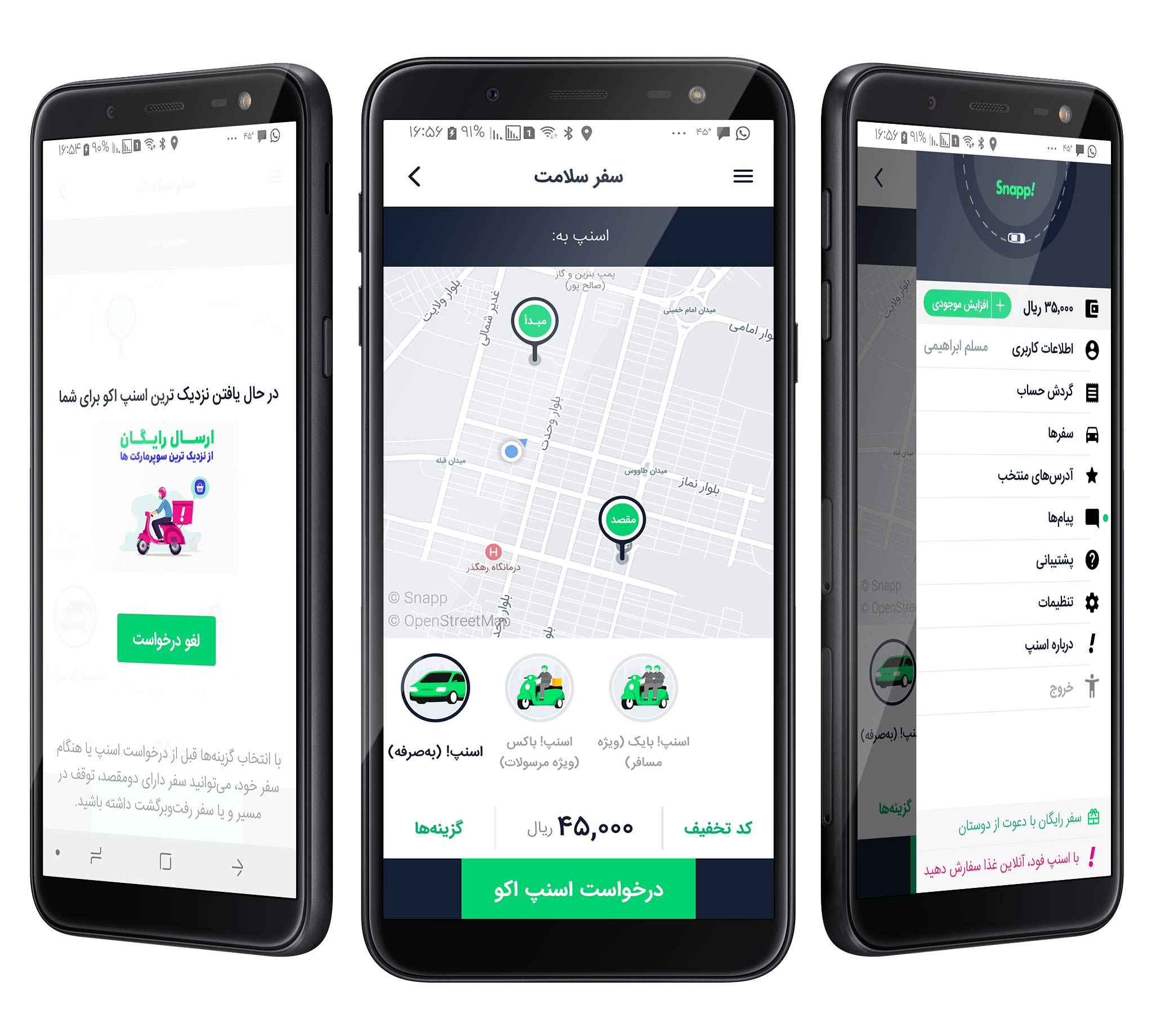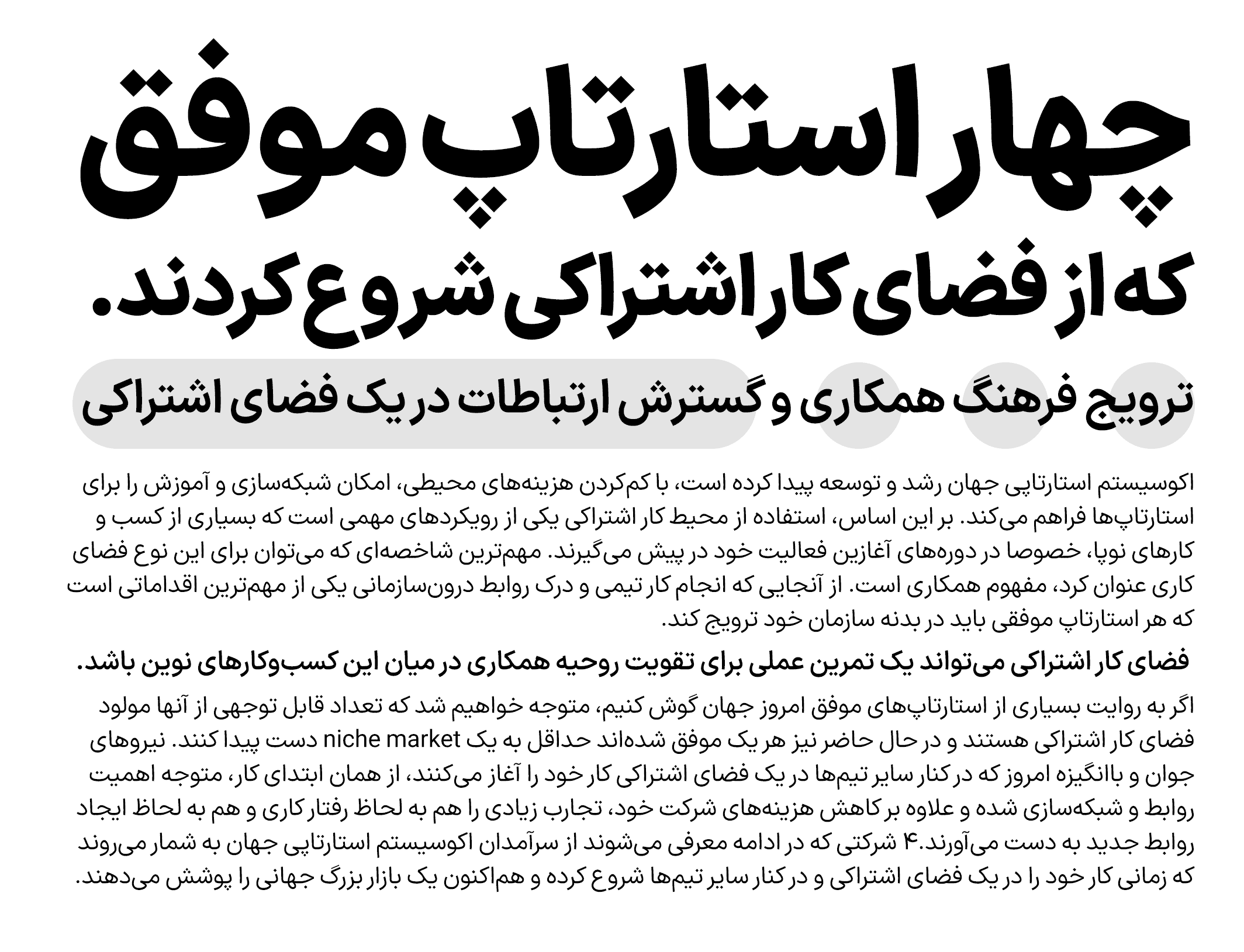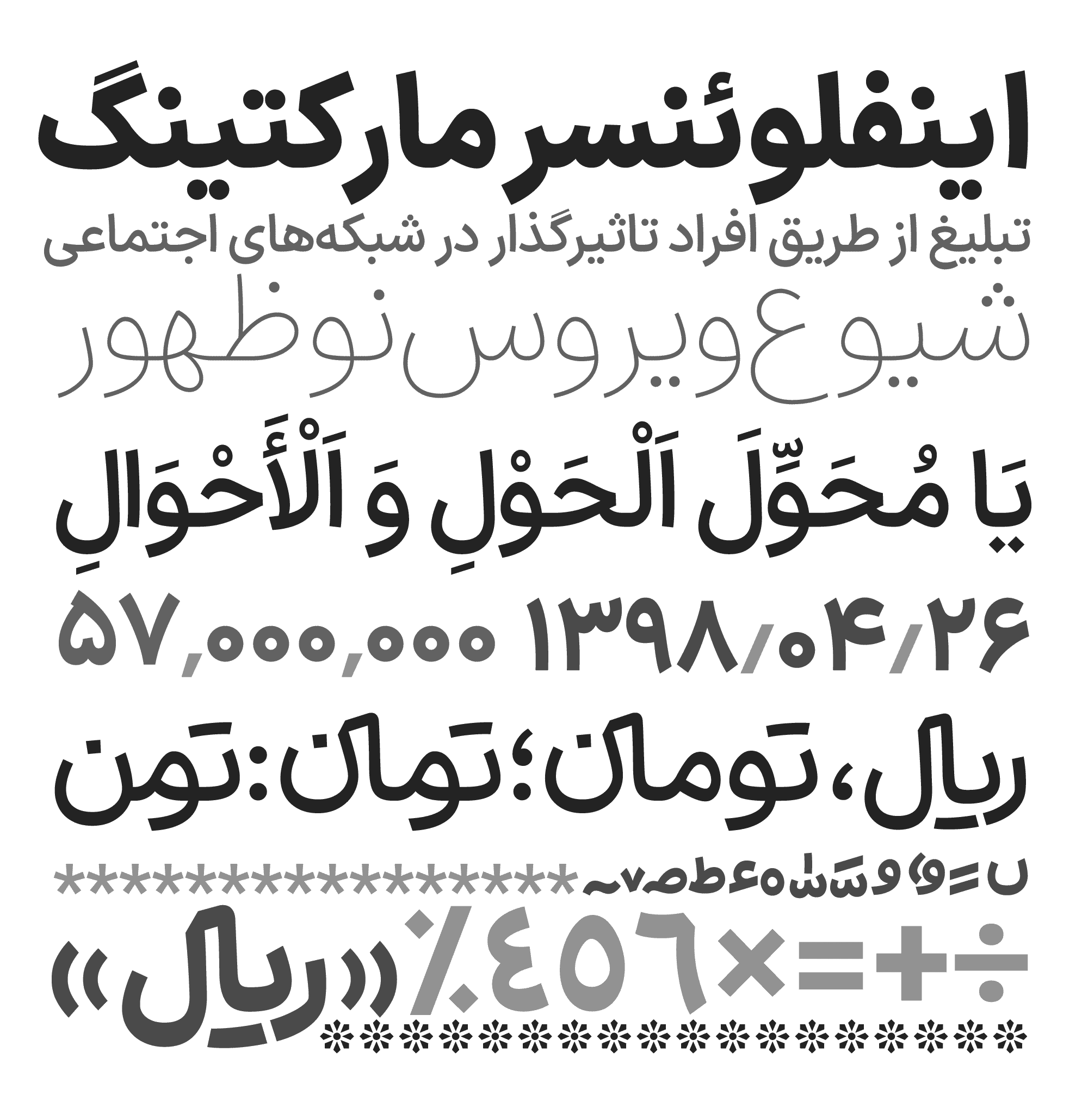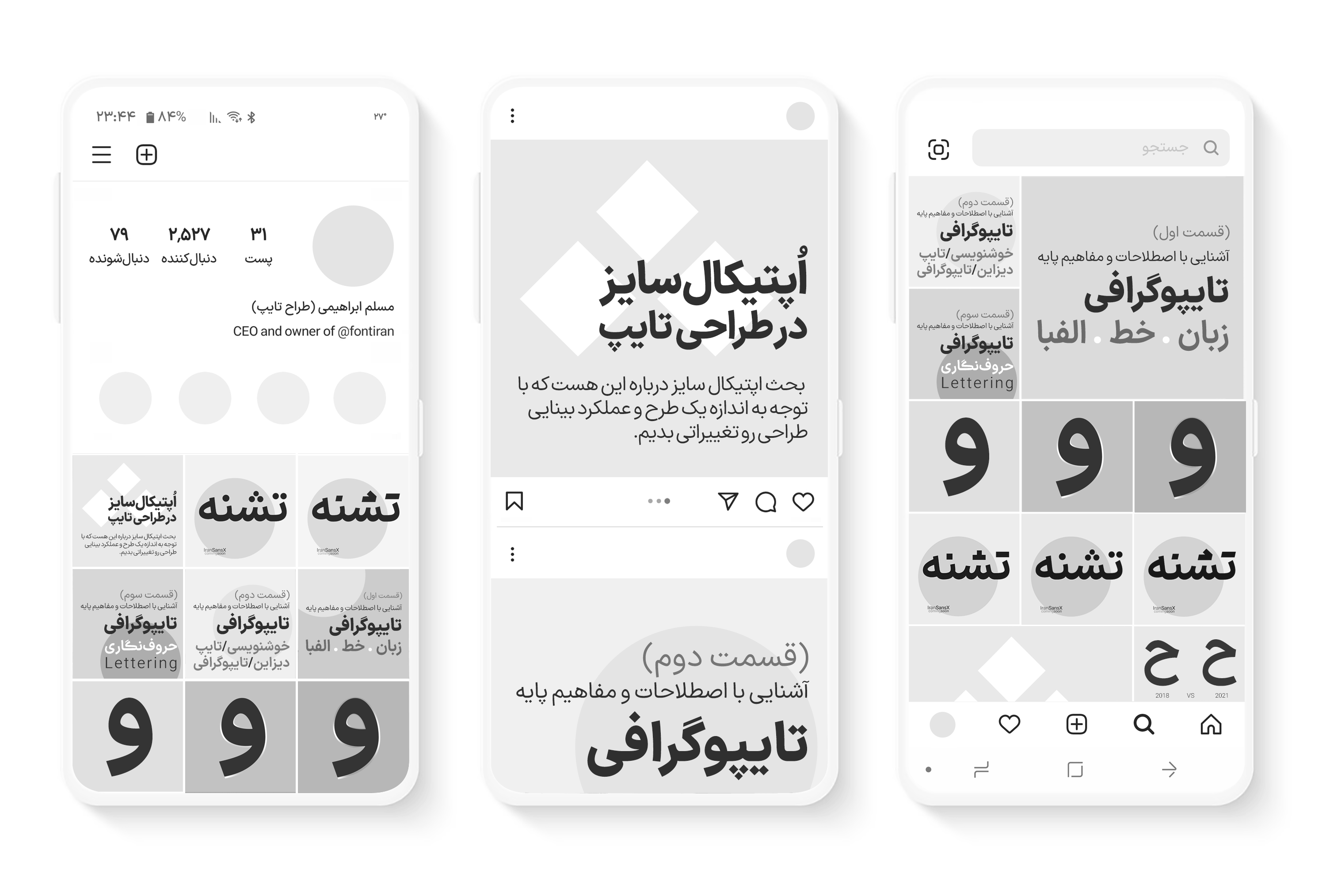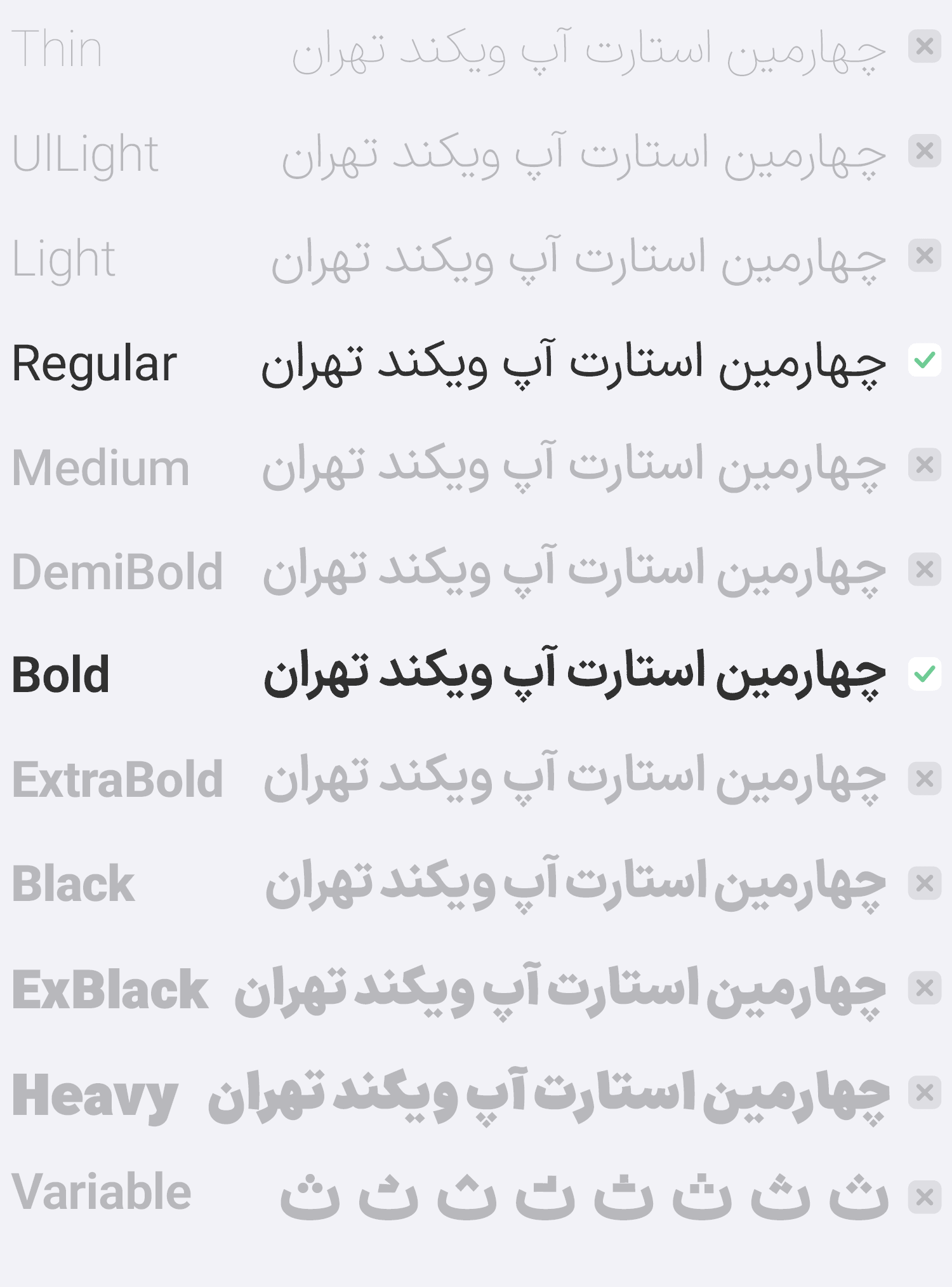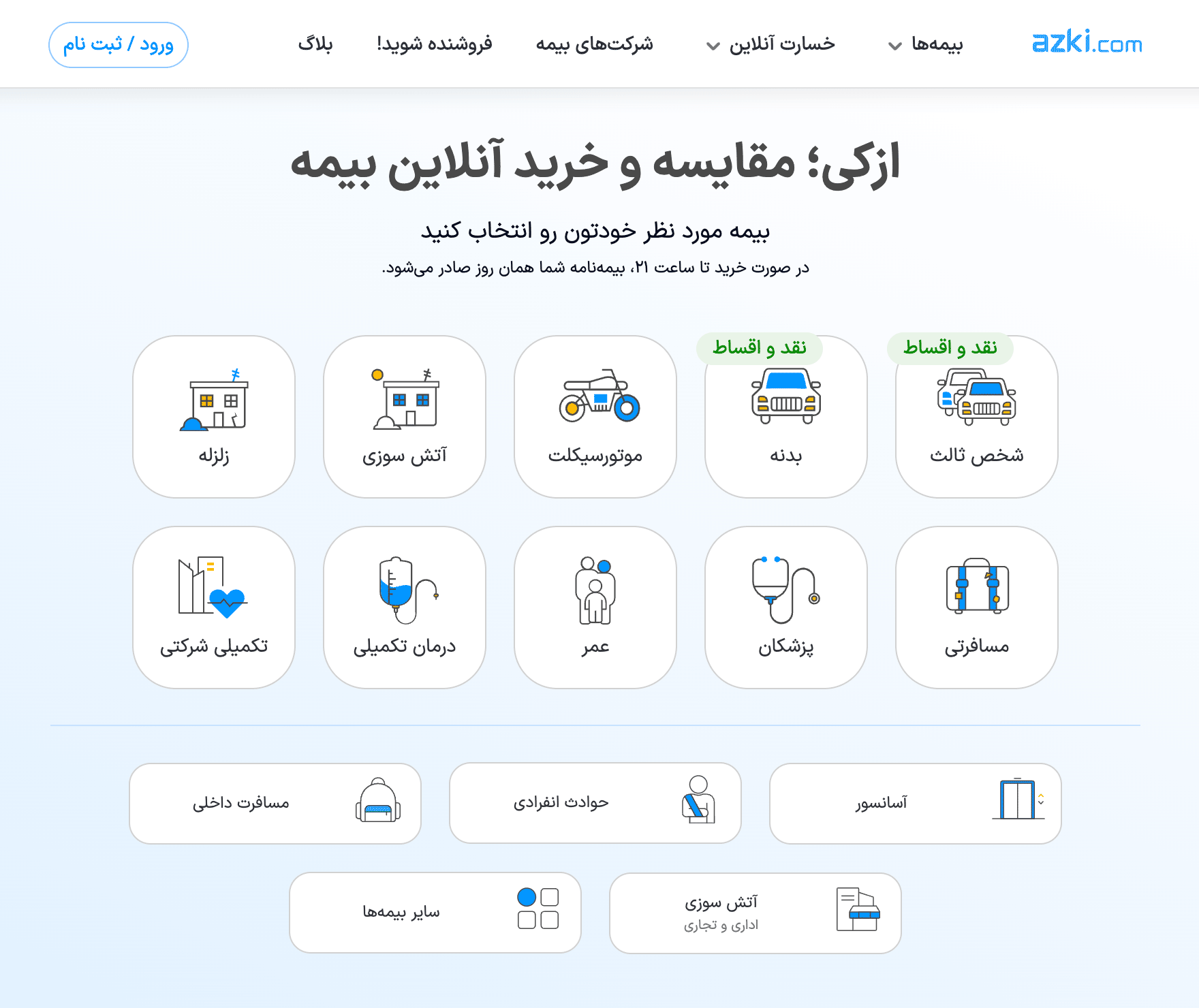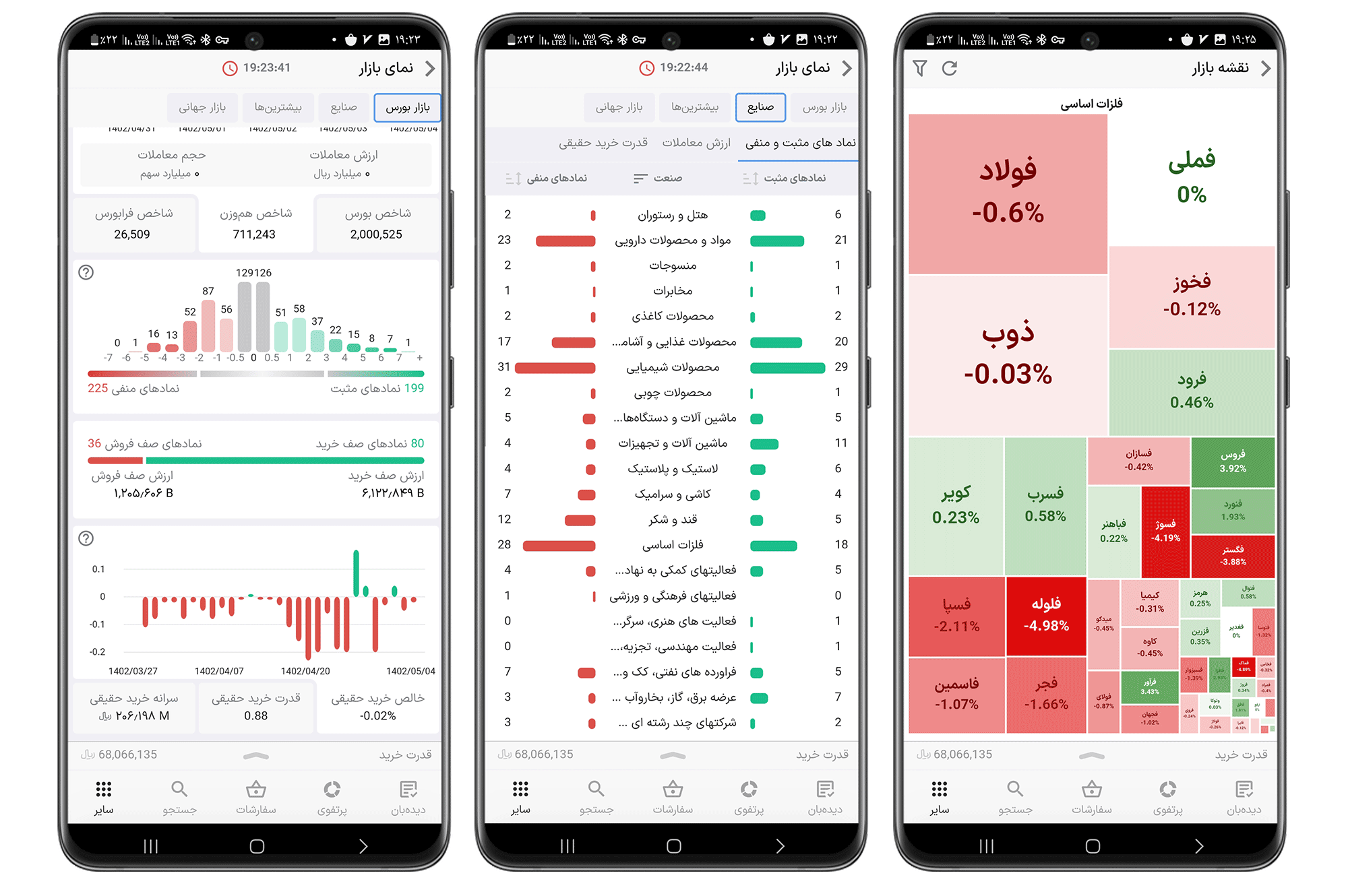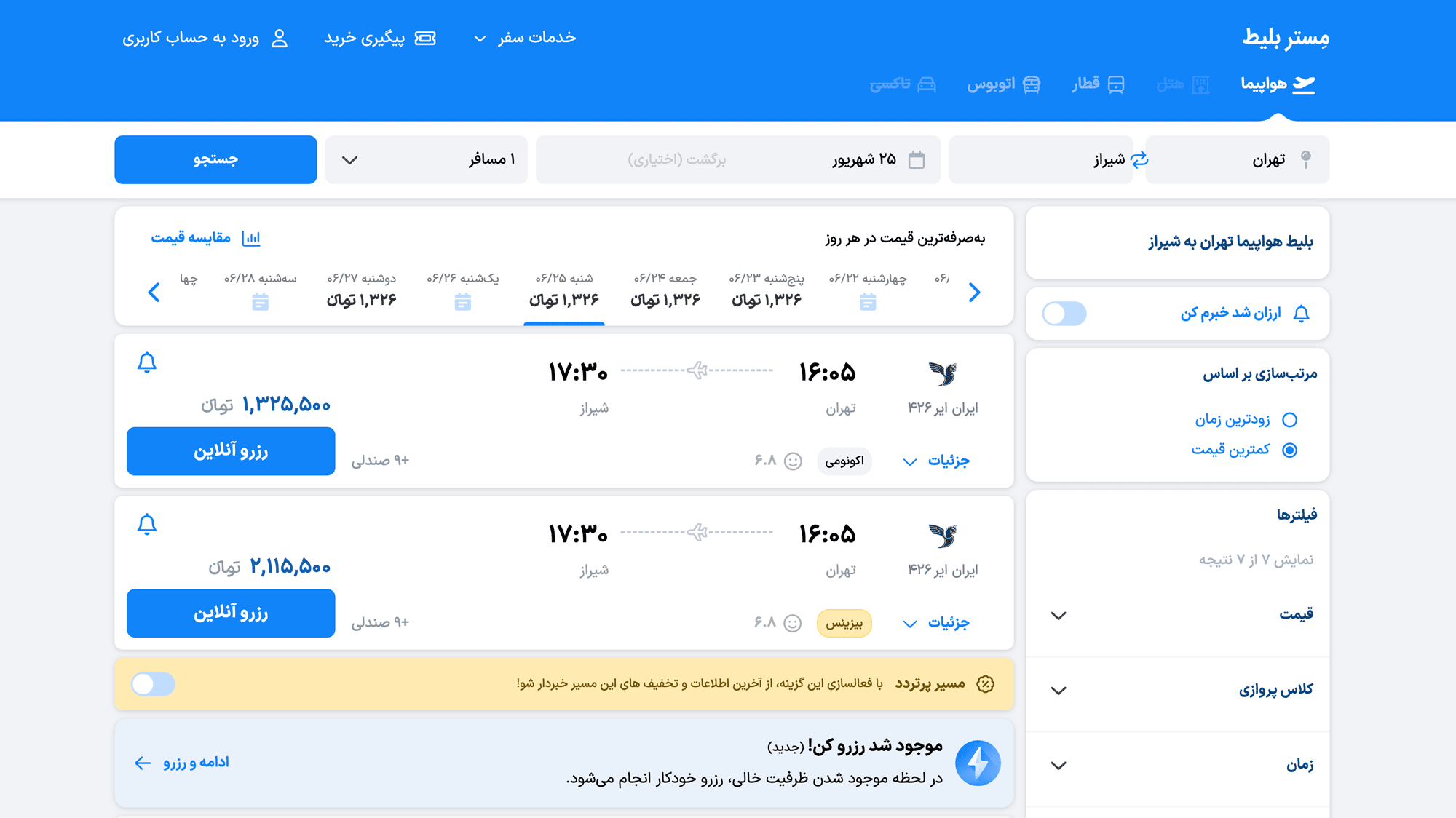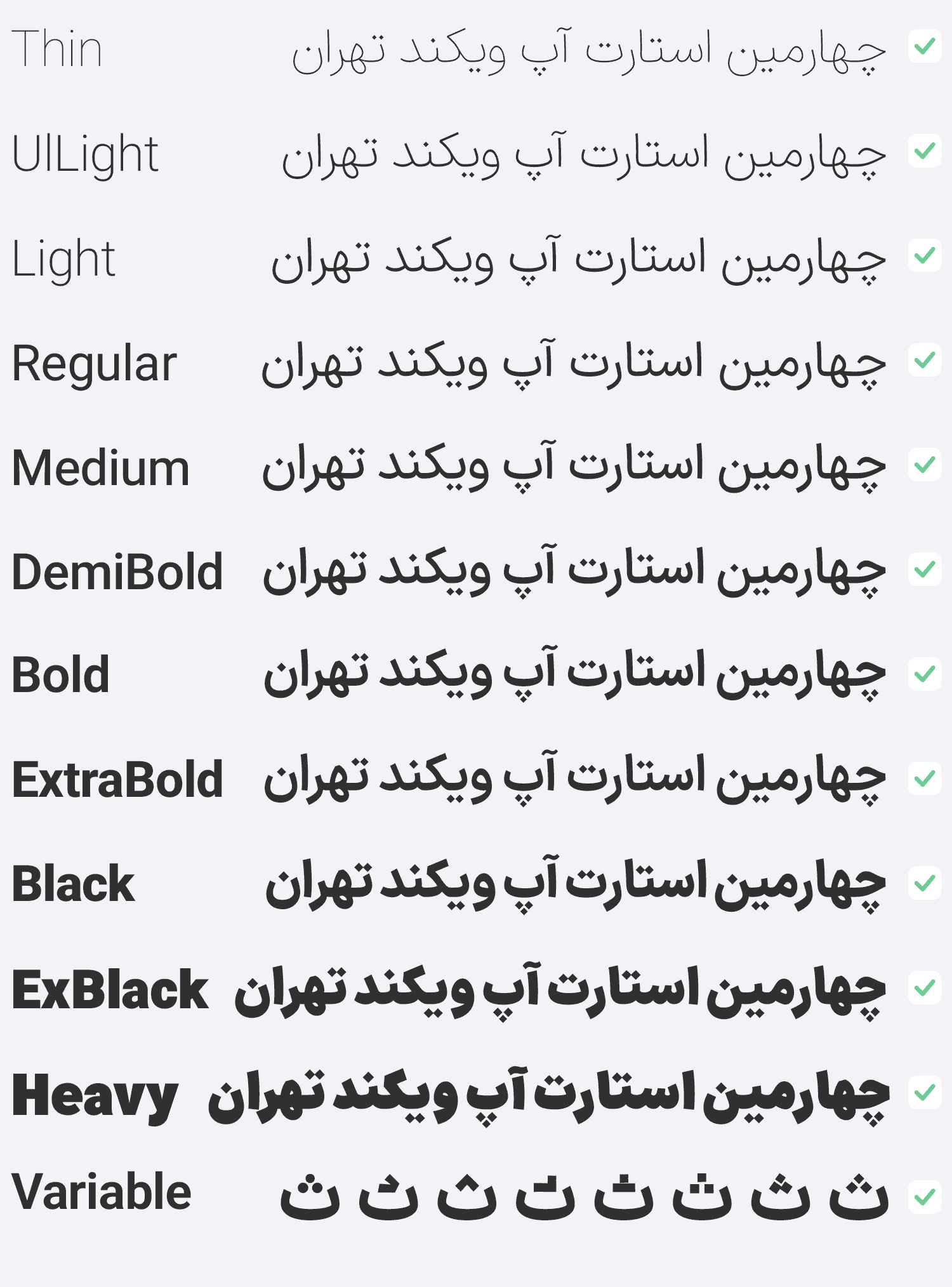
فونت ایران‌سنس
فونت ایران سنس پرطرفدارترین فونت فارسی در سال‌های اخیر بوده است.
اسنپ، دیوار، آپارات و صدها وب سایت و اپلیکیشن برتر ایرانی از ایران سنس استفاده می‌کنند.
3. وریبل فونت: فونت‌های متغیر دارای ۲ محور: تغییر وزن /  تغییر شکل نقطه‌های به ۹ حالت
ایران سنس X تایپ‌فیسی معاصر است که ریشه در میراث خط نسخ دارد. صورتی مدرن و مینیمال دارد اما در سیرت پیرو ساختار خوشنویسی است. در شکل حروف ایران‌سنس حداقل شکستگی و مسیر مستقیم دیده می‌شود. گردش‌های زیاد و پرهیز از قالب‌های هندسی نیز حس و حال انسانی و طبیعی ایران ‌سنس را قوی ‌تر می‌کند. نسبت‌ها و شکل حروف هم تا جای ممکن ساده و معمولی طراحی شده است تا خوانایی و روان‌خوانی در ایران‌سنس به حد اعلای خود برسد.
تنوع وزن‌ها در فونت ایران‌سنس iransansX
در فونت ایران سنس شما طیف کاملی از ۱۱ وزن را در اختیار دارید. همه این وزن‌ها دارای اسکلت و ساختار مشترک هستند و با افزایش وزن تناسبات حروف تغییر نمی‌کند.
نسخه‌‌ی قدیمی ایران‌سنس فقط حاوی ۶ وزن است و هماهنگی وزن‌ها به دقت نسخه‌ی جدید نیست.
علاوه بر ۱۱ وزن، یک استایل نقطه پیوسته نیز در بستهٔ حرفه‌ای فونت ایران‌سنس موجود است.
داستان ایران‌سنس
سال ۱۳۹۳ زمانی بود که اکوسیستم کسب و کارهای استارتاپیِ ایران در حال بالندگی و رشد بود. فونت‌ ایران‌سنس نخستین بار در همان سال (۱۳۹۳) منتشر شد.
طراحانی که در این شرکت‌های استارت‌آپی مشغول به کار بودند به نسبت دیگر طراحان نگاهی کاربردی به فونت فارسی داشتند و جسارت بیشتر در استفاده از فونت‌های جدید داشتند. بنابراین فونت‌ایران سنس در آغاز بیشتر از همه در طراحی وبسایت‌ها و نرم افزارهای شرکت‌های استارت‌آپی مانند دیجی‌کالا، کافه‌بازار، صبا‌ایده (آپارات)، اسنپ و … مورد استفاده قرار گرفت و تبدیل به نشانه‌ای از جامعه کسب و کارهای استارت‌آپی در ایران شد.
فونت متغیر (وریبل فونت)
وریبل فونت تکنولوژی جدیدی در ساخت فونت است که به شما این امکان را می‌دهد که همه‌ی وزن‌ها و استایل‌ها را در قالب یک فایل فونت در اختیار داشته باشید. فونت متغیر قطعاً بهترین گزینه برای ساخت وبسایت‌های جدید است. استفاده از فقط یک فایل فونت برای همه وزن‌ها و استایل‌ها باعث می‌شود فقط یک درخواست به سمت سرور شما ارسال شود و سرعت لود هر صفحه سریعتر باشد.
Weight : این متغیر وزن (ضخامت) نوشته را تعیین می‌کند که حداقل آن 100 معادل وزن Thin و حداکثر آن 1000 معادل وزن Heavy است.
Dots : این متغیر شکل نقطه حروف را به ۹ حالت مختلف تغییر می‌دهد.
چینش دقیق نقطه‌ها و دندانه‌ها
به دلیل وجود محدودیت‌های حروفچینی در دستگاه‌های اولیه چاپ جای نقطه‌ها مایل به راست است و این رسم در فونت‌های دیجیتال نیز باقی مانده است.
در فونت ایران سنس iransansX نقطه‌ها در جای درست خود یعنی زیر حرف مربوط به آن قرار دارند.
حروفی مانند ب‍ ‍ب‍ ت‍ ‍ت‍ پ‍ ‍پ‍ ث‍ ‍ث‍ ن‍ ‍ن‍ ی‍ ‍ی‍ س‍ ‍س‍ ش‍ ‍ش‍ گروه پر جمعیت خط فارسی هستند که شکل کاملا مشابهی دارند.  چشم تنها با تشخیص نقطه‌ها آن‌ها را از هم تشخیص می‌دهد.
در فونت ایران سنس iransansX  هر دندانه با توجه به حروف قبل و بعد خود جای نقطهٔ خود را طوری تعیین می‌کند تا نهایت نظم و زیبایی در شکل کلمات بدست آید.
در فونت ایران‌سنس IranSansX نقطه‌ها بصورت برنامه‌ریزی شده در محل ایده‌آل قرار می گیرند. بدون اینکه عرض حروف زیادتر شود یا فضای خالی بیش از حد پدید آید.
از فونت‌های هک شده خداحافظی کنید!
طراحان وب و نرم افزار در مواردی برای فارسی کردن اعداد نیازمند فونتی هستند که اعداد انگلیسی را فارسی نشان بدهد. این فونت‌ها در واقع فونت‌های هک شده هستند و دردسرهای زیادی برای وبسایت ایجاد می‌کنند. اگر از این فونت در وبسایت خود استفاده کنید دیگر اعداد انگلیسی نخواهید داشت و همچنین در سئو و سرچ وبسایت مشکلاتی ایجاد خواهد شد. این مشکلات سازندگان وبسایت را ناچار می‌کند که چند فایل فونت را بارگذاری کنند و این به معنی افزایش حجم بیشتر صفحه خواهد بود.
مسلم ابراهیمی
طراح فونت
مسلم ابراهیمی کارشناس ارشد گرافیک است که از سال ۱۳۸۸ بصورت پیگیر و حرفه‌ای به طراحی تایپ فارسی مشغول بوده است. در سال‌های ابتدایی دغدغه او تدریس طراحی تایپ در دانشگاه‌ بود و پس از آن با راه اندازی وبسایت فونت‌ایران تمرکز خود را به ساز و کار نشر و بازاریابی برای فونت فارسی تغییر داد. فونت‌های طراحی شده توسط مسلم ابراهیمی طی سال‌های ۱۳۹۳ تا ۱۳۹۶ توانست چهرهٔ تایپوگرافی وب و نرم‌افزار فارسی را تغییر دهد. مسلم ابراهیمی با راه اندازی وبسایت فونت‌ایران توانست فرهنگ رعایت داوطلبانه کپی رایت فونت را در ایران رواج دهد و چالش‌های فروش و کسب درآمد برای طراحان تایپ ایرانی را حل کند. :: فونت ایران‌سنس از ساخته‌‌های مسلم ابراهیمی پر استفاده‌ترین فونت وب و نرم افزار در ایران است. :: مسلم ابراهیمی در سال ۲۰۲۴ با فونت هستی توانست مقام دوم رقابت جهانی گرانشان را کسب کند.